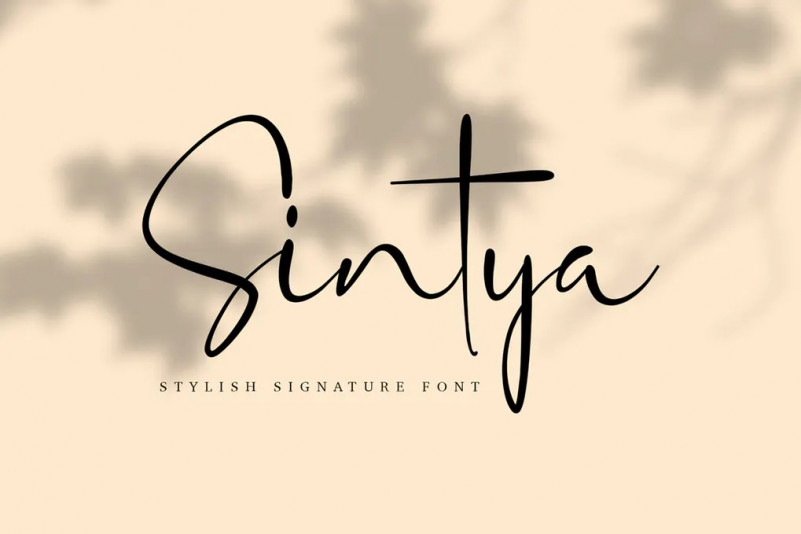
Sintya Font
Une police signature élégante, moderne et belle lettrée à la main avec une touche élégante. La police Sintya est parfaite pour les projets d’affichage tels que le texte cité, le nom du produit, le Logo, le profil, la boutique, l’invitation de mariage et bien plus encore. Il est également parfait pour la mode et la beauté sur le thème – ou un texte élégant superposé à n’importe quelle image de fond.